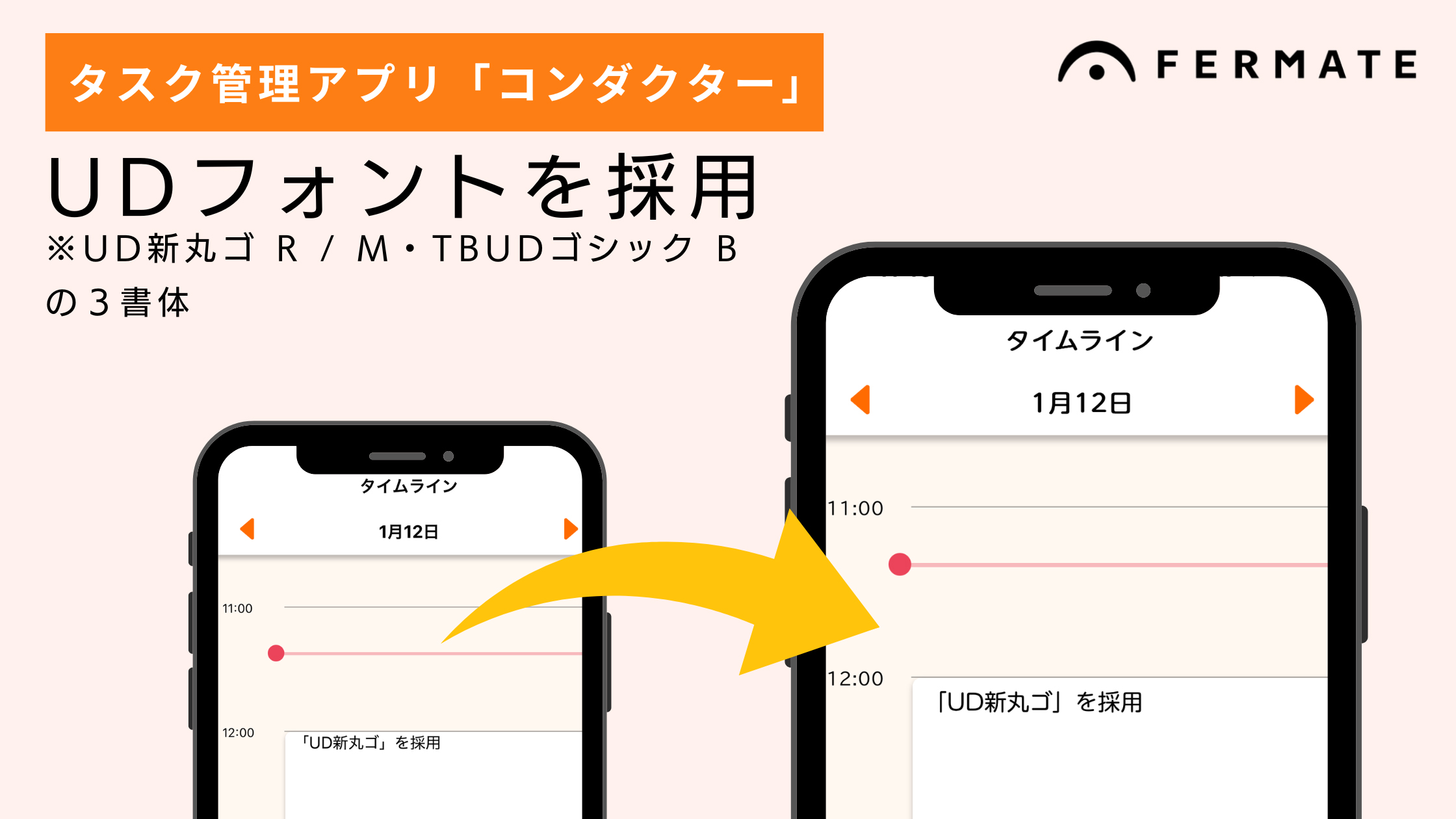
「ITやデザインの力で誰もが
活躍できる社会を作ること」
を理念に
フェルマータ合同会社は「ITやデザインの力で誰もが活躍できる社会を作ること」を理念に活動する会社です。発達障害当事者の職場環境を改善するアプリケーション「コンダクター」を開発しています。その他、大学やNPO、企業向けのWeb制作、サイトやシステム保守、IT全般に関する相談を受ける「ITサポート事業」を行なっています。社名の“フェルマータ”は音を伸ばす音楽記号からきており、「ITを掛け合わせて可能性を伸ばす」という意味が込められています。
2021年4月にフェルマータ合同会社を設立。WEBシステム・WEBサイト制作のほかに、発達障害者を含む就労支援の相談員としての顔をもつ、同社代表の寺戸慎也氏に会社の事業とフォント採用の経緯についてお話を伺いました。
フェルマータ合同会社について
寺戸氏:私たちフェルマータ合同会社は、ハッタツソン2019という発達障害当事者に関する課題を解決するためのハッカソンイベントで生まれたアイデアが基となり、立ち上げた会社です。私たちフェルマータの原点です。現在、共同代表を務める森本をはじめ発達障害当事者やエンジニア、デザイナーがチームとなって意見を出し合い、タスク管理アプリ「コンダクター」の企画を考案しました。更に検討を重ねて、クラウドファンディングを成功させるなど、約3年の歳月をかけリリースできたのが「コンダクター」です。
- ※ハッタツソンとは、「ひとりひとりが過ごしやすい社会をともにつくる」を目標に感覚過敏や見えづらい違いなど、多様な認知特性を持つ人々が共に創り上げるイベントです。当事者の方や、当事者とかかわりのある人には、必要な情報や選択肢に触れられる場であり、また企業にとっても様々な目線で情報が発信・共有できる、新たなヒントを得る場にもなっています。
- ※ハッカソンとは「ハック(hack)」と「マラソン(marathon)」を掛け合わせた造語で、限られた短い期間で、エンジニアやデザイナー、プランナーなどからなるチームを編成し、企画開発を競い合うイベントです。
タスク管理アプリ「コンダクター」とは
発達障害の特性によっては、働くなかで「曖昧な指示がわかりにくい」「時間管理が難しい」など、仕事上の問題が起きることがあります。
タスク管理アプリ「コンダクター」は「1日のタスク(やるべきこと)をタイムラインで表示して見通しを立てやすくする」アプリケーションです。仕事の終了条件を設定することで達成感を得られる機能もあります。
寺戸氏:学校での学習とは異なり、仕事になると、自身で優先度を考えて組み立てることや、明確な正解がない場合が多いです。そのため、学生時代は成績優秀な方でも、働く環境によっては特性との不一致を起こし、社会に出てからご自身の特性に気がつく方や、発達障害の診断はされなくとも、いわゆる「グレーゾーン」で、困りごとを抱える方もいらっしゃいます。
特性や困りごとは様々ですが、長年現場に携わってきた経験から、この「コンダクター」は代表的な発達障害であるADHD(注意欠如・多動症)、ASD(自閉スペクトラム症)の方が使いやすいように工夫しました。
【ADHDとASDに共通した主な特性】
①注意力の運用
②情報の判断
③時間的展望の持ちづらさ など
双方が持つこれらを合わせた実行機能(課題を段取りよくこなすことができる能力)にアプローチすることで職場環境や働きにくさの改善を目指しています。
「コンダクター」のタスク管理機能によって、働く人が「今、自分が何に集中すべきか」の把握を視覚的にわかりやすくすることで、業務遂行を支援したいと考えています。
「生活全体」を大切にしてほしい
寺戸氏:仕事だけでなく、プライベートも含めて一元管理できるようにしたことも「コンダクター」の特徴です。ハッタツソン2019の時もチーム内で様々な意見がありましたが、「生活全体」を大切にしてほしいという思いから議論の末に実装しました。
ユーザー層は子どもから大人まで幅広く、グループホームや生活支援を受ける方々にもご利用いただけるのではないかと思います。
私自身も「コンダクター」を利用し、訪問先や事務所への移動を含めたスケジュールの調整や、タスクの管理に役立てています。エネルギーが溢れて注意力が散漫しやすい特性がありますが、タスク管理をすることで冷静に物事を進めることができます。
アプリ開発の目的とマッチした、UDフォントの採用はマスト
寺戸氏:まずは読みやすいかどうか=可読性・視認性が最重要だと思っています。その上でデザイン性もついてくるのが理想です。UDフォントは多くの方に読みやすく分かりやすいデザインを目指して設計している点が、「コンダクター」の開発の目的とマッチしていると思い、予算と時間をかけてでも、絶対に採用したいと強く思いました。
どのフォントで、どのウエイト(太さ、黒み)が適しているのか、様々なパターンや端末で何度もテストした結果、今回はUD新丸ゴとTBUDゴシックの2書体を採用しました。
ハッタツソンフェス2024のモリサワの出展ブースでUDフォントを知り、その後画面表示のテストなど調整を進め、ハッタツソンフェス2025でようやくアプリのリリースを発表することができました。時間はかかりましたが、やはりこだわってよかったです。
かつての「眼鏡」がそうだったように、テクノロジーは環境を変え、障害を無くすことができる
寺戸氏:障害があっても誰もが可能性を発揮し、働くことができる環境を作ることが目標です。
現在、フェルマータは法人化していますが、元々は任意団体でメンバーそれぞれに本業があったため、牛歩のような歩みでしたが、決して止まる事なく開発を進め、資金集めのクラウドファンディングなども実施しました。
2021年4月のβ版のリリース後、ハッカソンからのグループは一度解散し、さらに開発を進めるための資金調達を目的に、私寺戸とエンジニアの森本が共同代表となり覚悟をもって法人化し、本格的なスタートを切りました。
クラウドファンディングを実施した際に、“子どもが大きくなった時に、働きやすい環境が整っていることを願って支援したい”という親御さんからのコメントに心を動かされたことも、私たちの原動力となっています。
事業は順調で、主に中小企業やNPOなど、小規模ですが社会的に意義ある事業をされている方々をITの力でサポートすることで、共に拡大・成長を目指しています。かつての「眼鏡」がそうだったように、テクノロジーは環境を変え、障害を無くすことができると私たちは信じています。事業の発展とともにアプリ開発も進めていきます。
また、【タスクの管理=時間の管理=注意力の管理】だと考えているので、今後は「トークンエコノミー」といって、タスクを達成したら、キャラクターが成長していくなど、モチベーションが上がるような機能も開発していきたいです。
モリサワに期待すること
寺戸氏:フォントを選ぶ際には可読性と視認性を最優先し、デザイン性と両立できるフォントを求めています。モリサワにはこの2つが両立したフォントを提供いただいて、今後もクリエイティブな仕事にインスピレーションを与え続けてくださることに期待しています。
また、「発達障害」の認知度はかなり上がってきていますが、学校など教育機関、また私が就労支援をしながら関わっている障害専門の部局でもその特性理解が十分とは言えません。「コンダクター」だけですべて解決できると思ってはいませんが、世の中での発達障害特性に関する理解がさらに広まり、それぞれが適した環境の中でいきいきと力を発揮できる社会の実現を目指して、ユーザーの声を反映し、改善し続けていきたいです。
モリサワには今後もUDフォントを中心としたフォントの分野で、当事者やそこに関わる人のために協力いただきたいです。そして、生活の中での困りごとや、働きたいという意欲や想いの支援に関わる「コンダクター」のような事例が増えると嬉しいです。